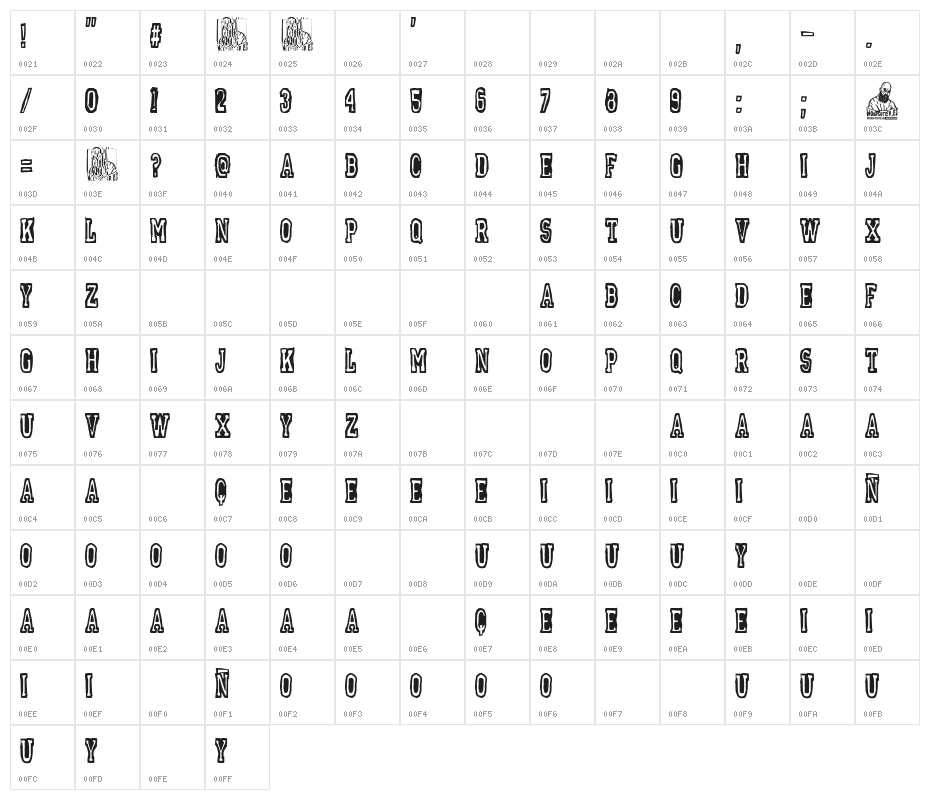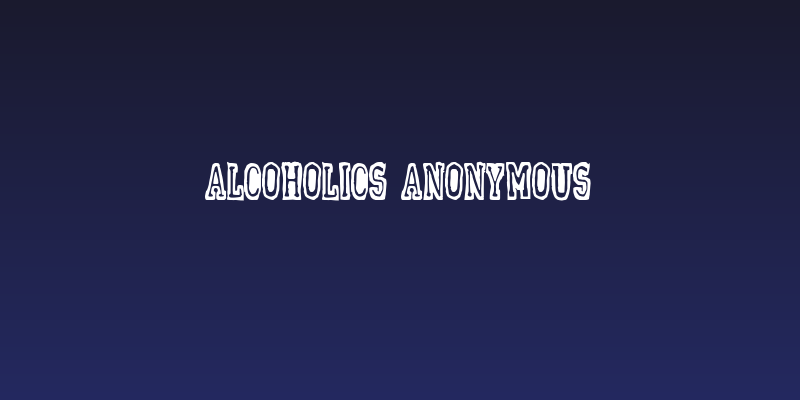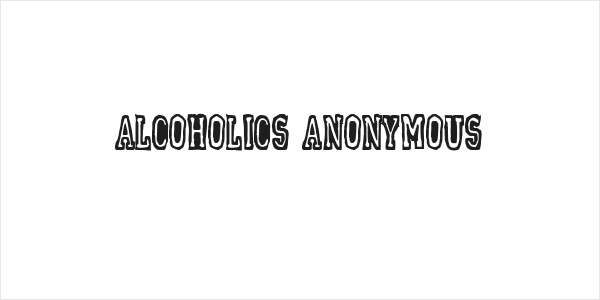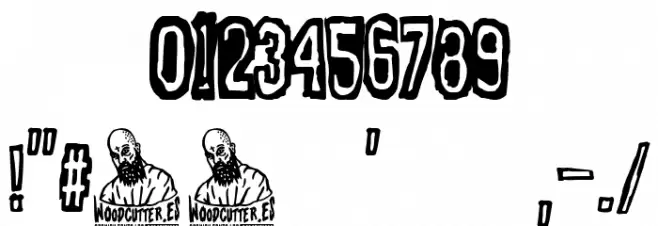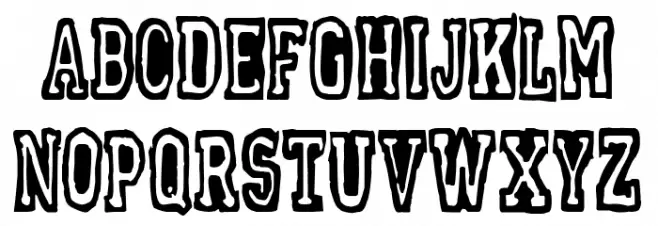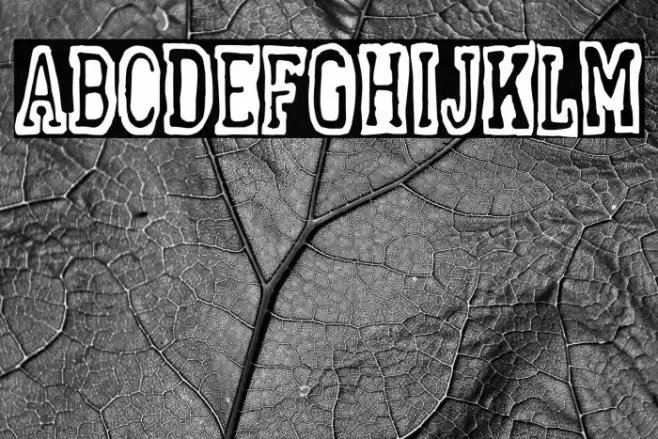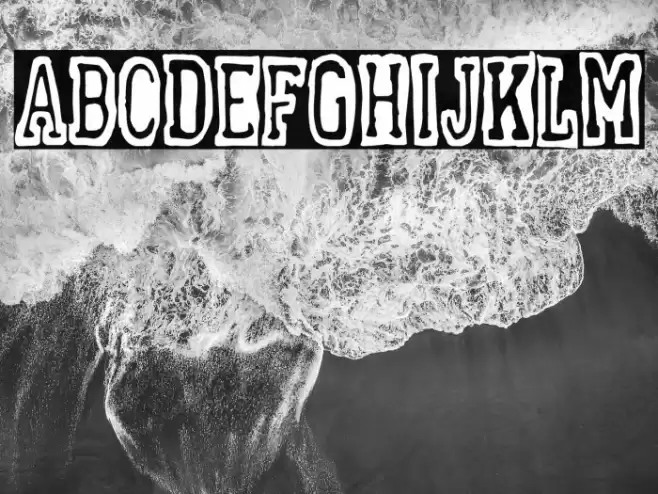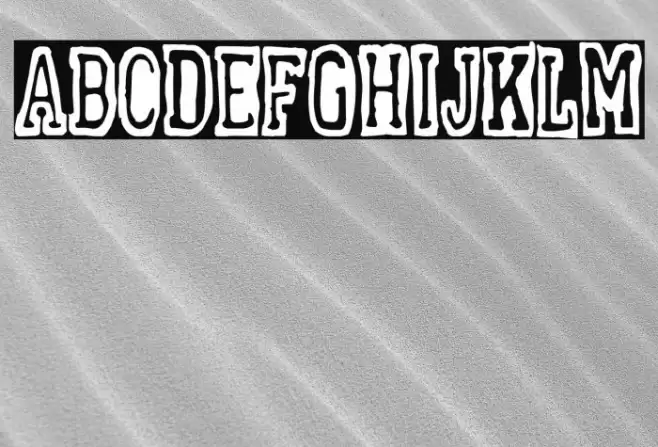
Alcoholics Anonymous Font
| Projets proposés | Ideal for vintage-themed posters, logos, and branding materials that require a rustic or handcrafted appearance. |